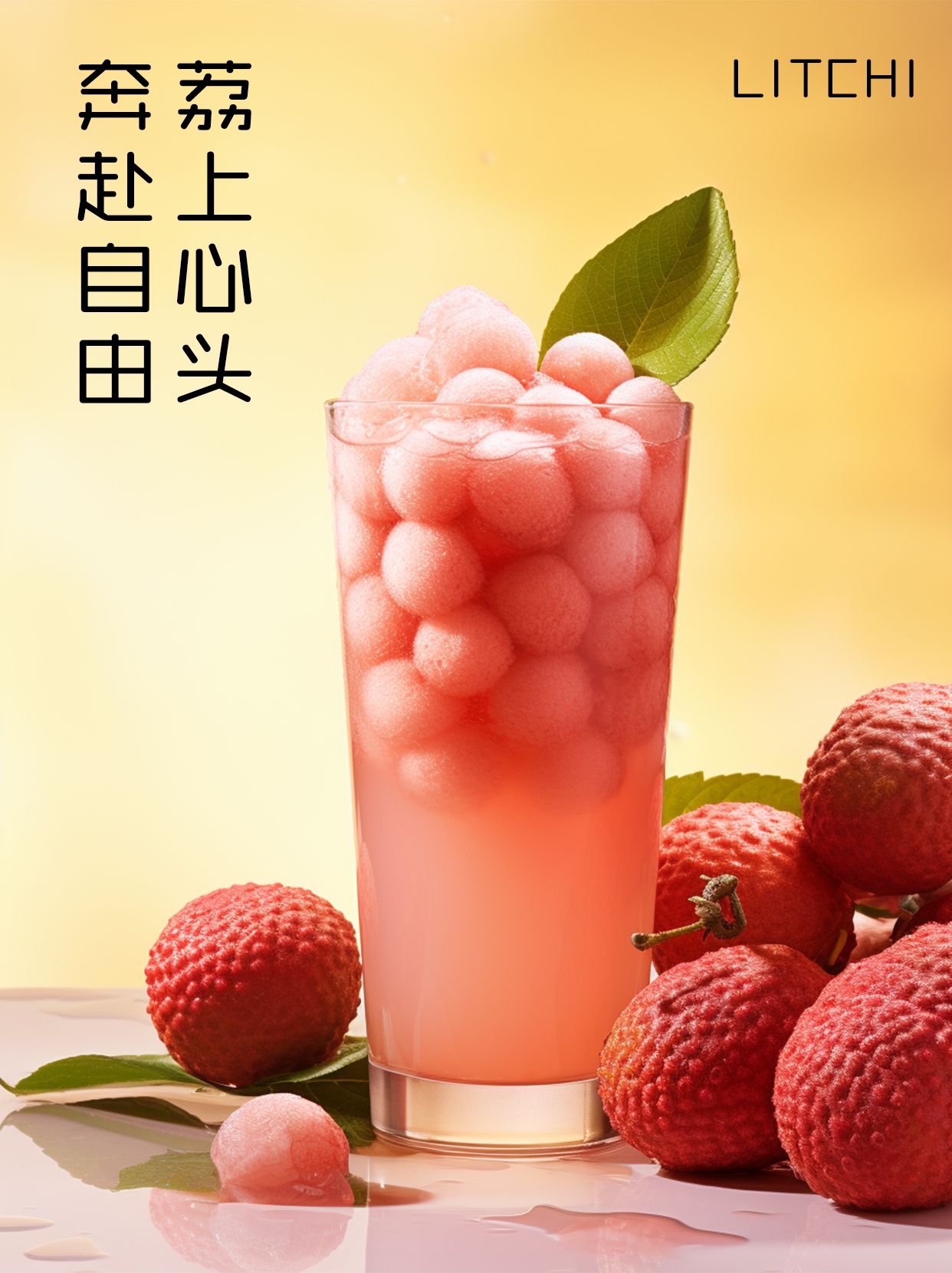
海报设计如何出圈?海报设计精选字体大公开!
在海报设计中,字体穿插是比较常见的一种手法。文字与植物相互层叠遮挡,让文字的部分更有立体感,画面也看起来会有空间感。如果是搭配人物动作的话,会让画面看起来更加动感。字体的识别性与内容传输能力是其他元素不具备的,励字造梦共创字库精选2款适配率高的海报字体,一键提升海报创意及吸睛度。
一款既有着严谨结构、又兼具优雅的黑体。现代几何化设计的笔画,给人舒适、柔和的视觉感受。
字型圆润柔和笔画为直线笔画,以竖折笔画代替部分弧线简洁明了。 笔画起笔、收笔和转折处融合圆体自然的圆弧风格,中宫松散,外圆内方。 此款字体是具有3款字重的家族字体,适用标题和正文,具有良好的视觉表现与阅读体验,可以适配多种风格与样式的排版。